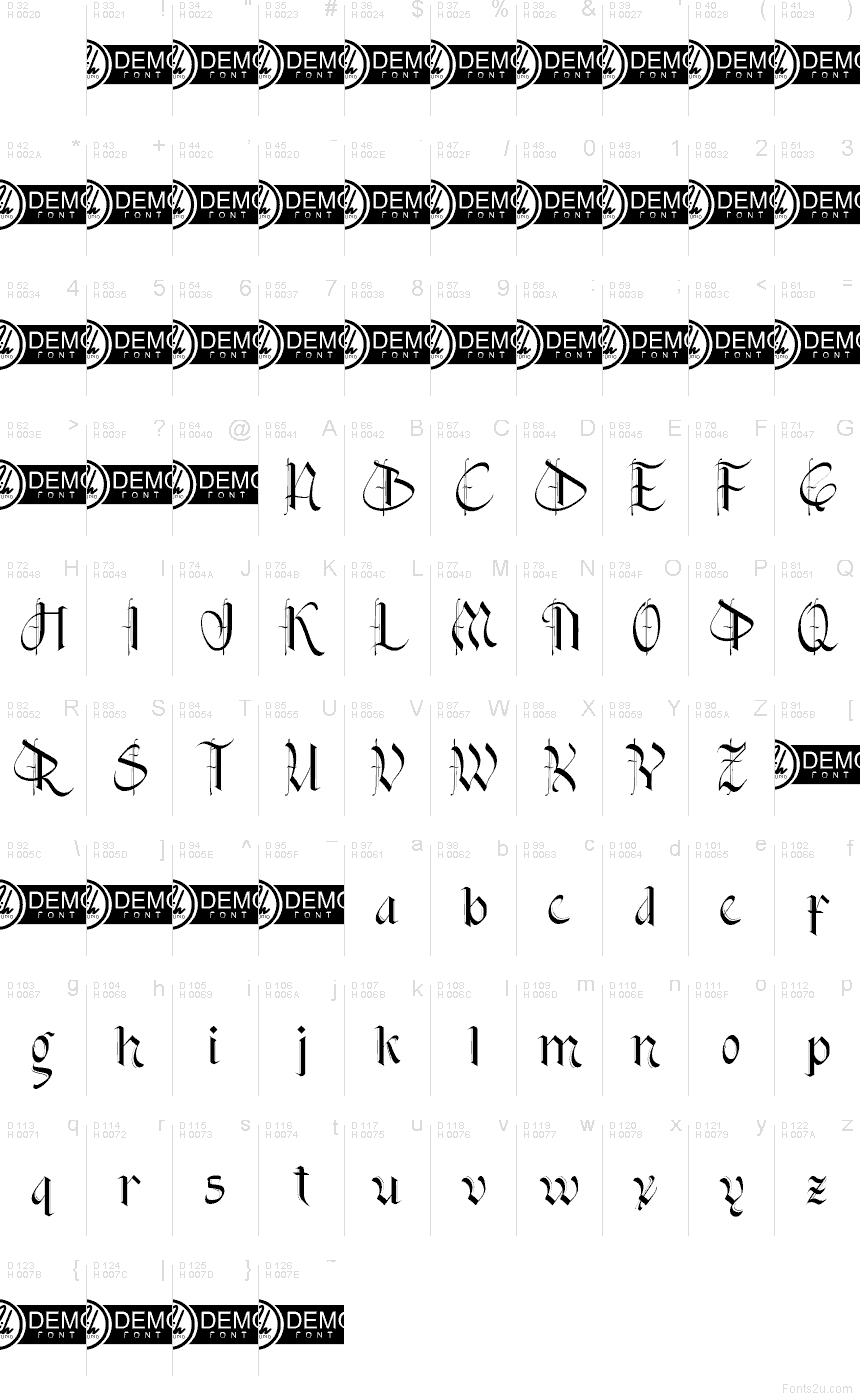
Black Gothics od NihStudio je bezplatné stredoveké gotické písmo s dramatickým nádychom štýlu blackletter a výraznými ornamentálnymi prvkami. Písmená kombinujú vysoké, ostré zvislé ťahy so širokými, zatočenými krivkami a detailmi v tvare slzy, vďaka čomu pôsobí celkový dojem skôr slávnostne než stroho.
Hodí sa na projekty, ktoré vyžadujú historickú váhu, no bez akademického pôsobenia: knižné obálky, festivalové či krčmové plagáty, logá kapiel, titulky a monogramy. Ako bezplatné písmo najlepšie funguje v krátkych nápisoch, kde majú jeho prepracované krivky a vyrezávané uhly priestor vyniknúť.